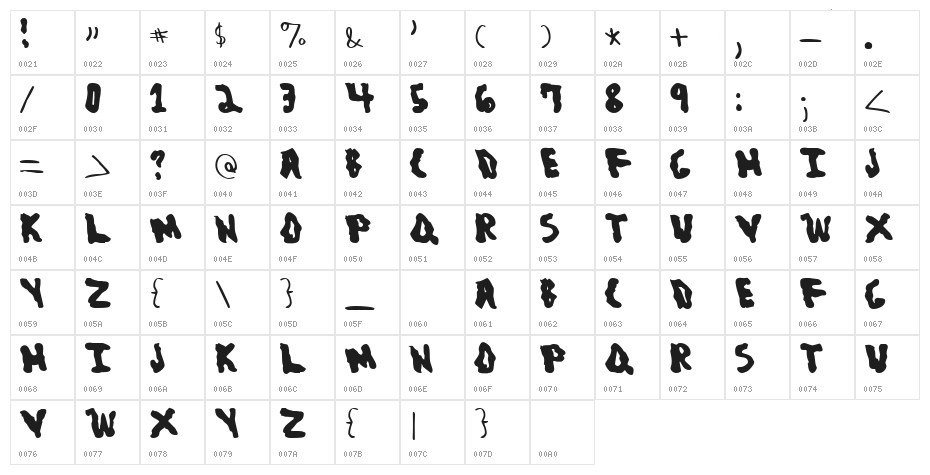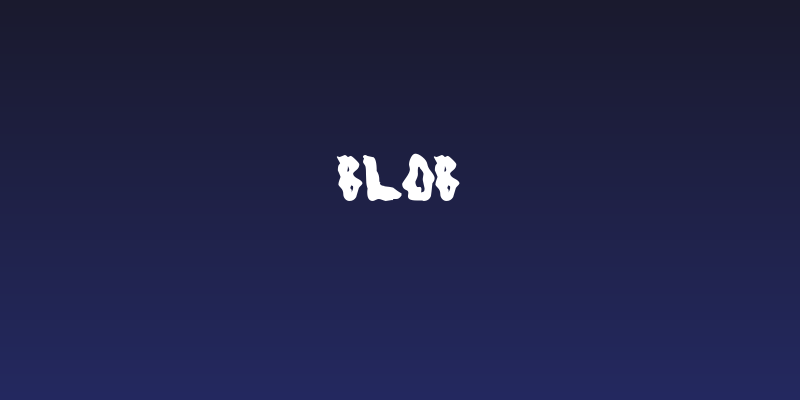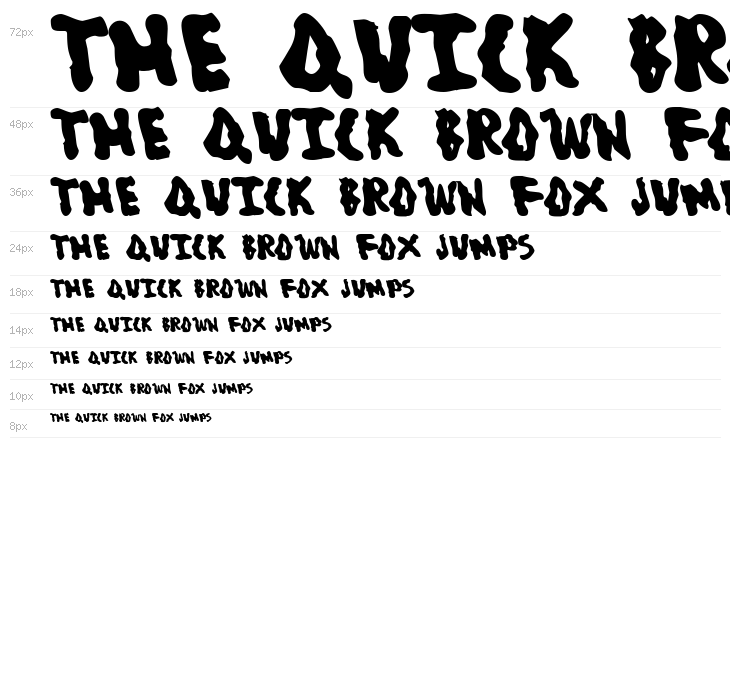
Blob Font
| Stile generale | Playful, Casual, Whimsical |
| Progetti proposti | Ideal for children's books, comic strips, playful branding, and casual invitations. |